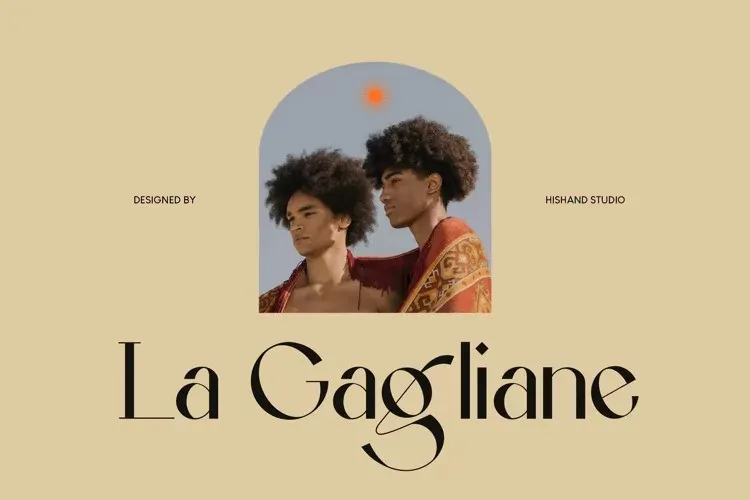
A La Gagliane Font é uma elegante tipografia sans serif criada pela Hishand Studio com ligaturas que resultam em citações estonteantes e postagens do blog perfeitas para logotipos, anúncios, embalagens de produtos, postagem no Facebook, roupas de marca, cabeçalhos de revistas e muito mais. Com seu design limpo e moderno, a La Gagliane é uma escolha perfeita para designers que desejam um texto contemporâneo em suas criações gráficas. Seu uso em diferentes ambientes permite não apenas criar estilos únicos de marca, mas também torna sua fonte versátil o suficiente para atender a uma variedade de necessidades em design gráfico. Engajante e funcional, La Gagliane é um recurso imprescindível para qualquer designer que busca adicionar uma pitada moderna à sua próxima peça de trabalho visual.